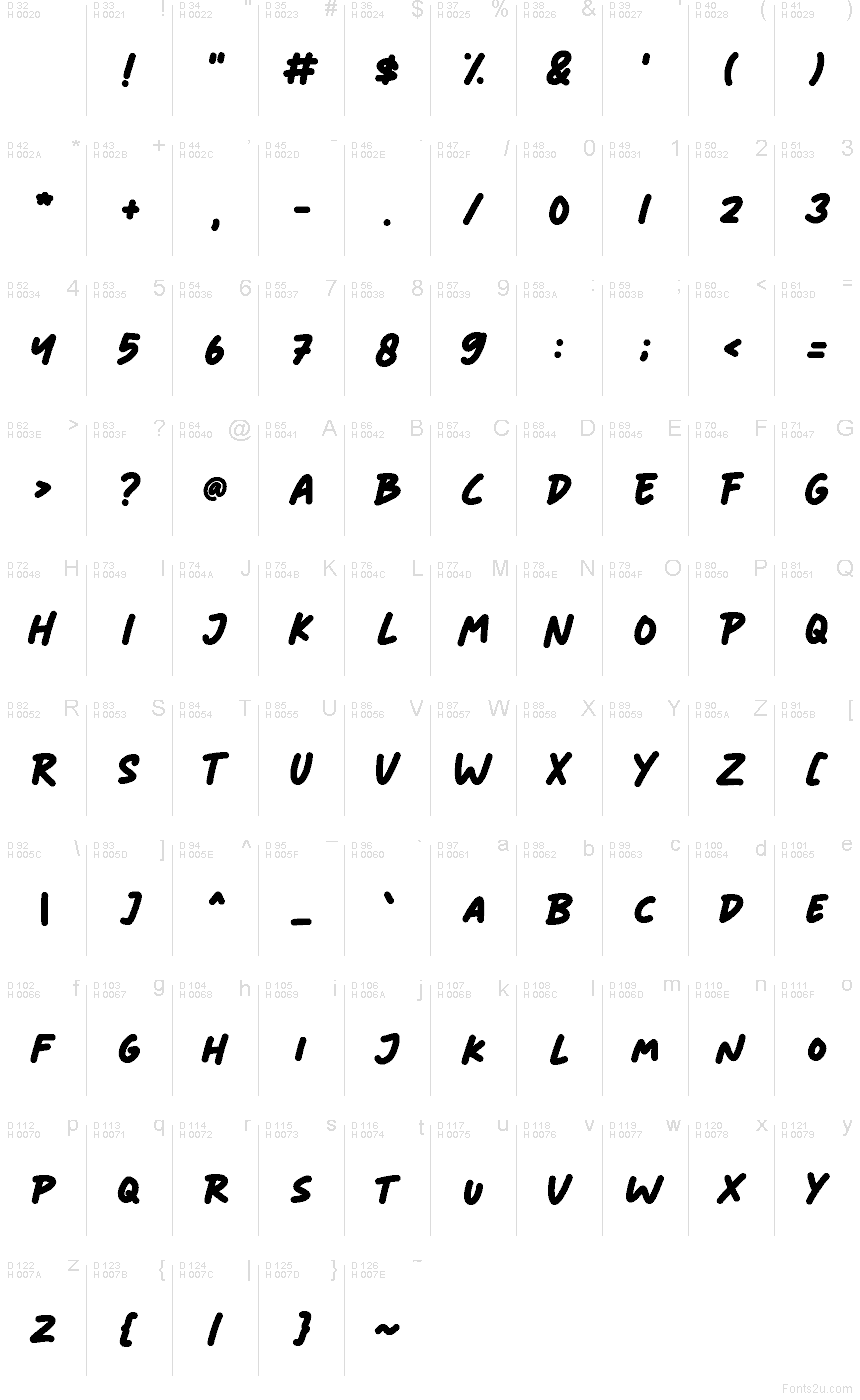
Enjoy Journey, stworzony przez Graphix Line Studio w 2022 roku, to darmowy, odręczny krój pisma typu display o szerokich, dynamicznych pociągnięciach przypominających liternictwo markerem. Zaokrąglone kształty, nieregularne kąty i łagodnie zmieniająca się grubość linii sprawiają, że litery wyglądają na szybko nakreślone, a zarazem pewnie uformowane.
Może zmienić logo lub etykietę produktu w radosny, odręczny napis, idealny zwłaszcza do przekąsek, zabawek czy odzieży codziennej. Te same masywne łuki pasują do publikacji dla dzieci i plakatów wydarzeń, gdzie liternictwo staje się częścią ilustrowanej tożsamości marki, a nie tylko jej nazwy.